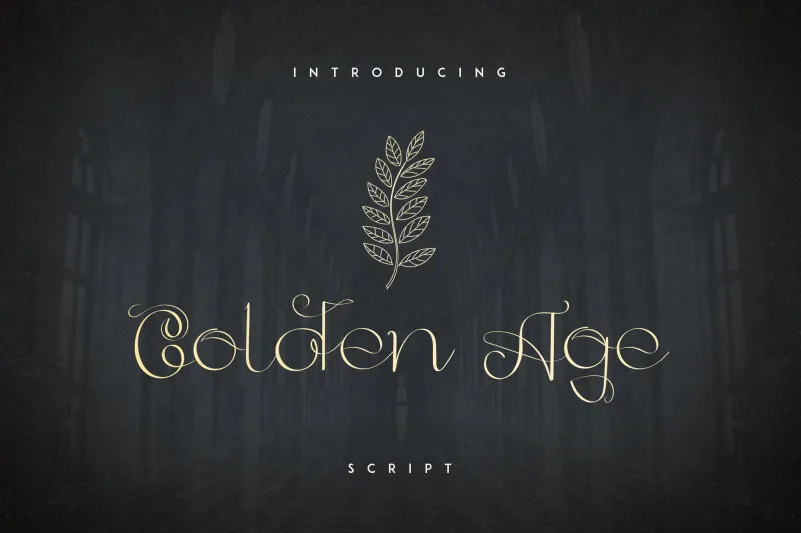
Golden Age Script Font – Download Grátis
Introduzimos a Golden Age Script Font, uma elegante fonte escrita à mão que transmite uma personalidade única e encantadora. Confeccionada com linhas secas e limpas, ela se destaca especialmente para projetos de marca, designs de produtos, embalagens de casa ou até mesmo como overlay estilizado ao texto de qualquer imagem de fundo. Ideal tanto para aplicar sobre imagens em preto e branco quanto sobre fotografias coloridas, a Golden Age Script Font é uma escolha ótima para aqueles que valorizam um toque autêntico no design visual. Não importa o projeto: seja ele impressão digital ou impressão física, ela certamente enriquecerá seu trabalho de forma única e memorável.